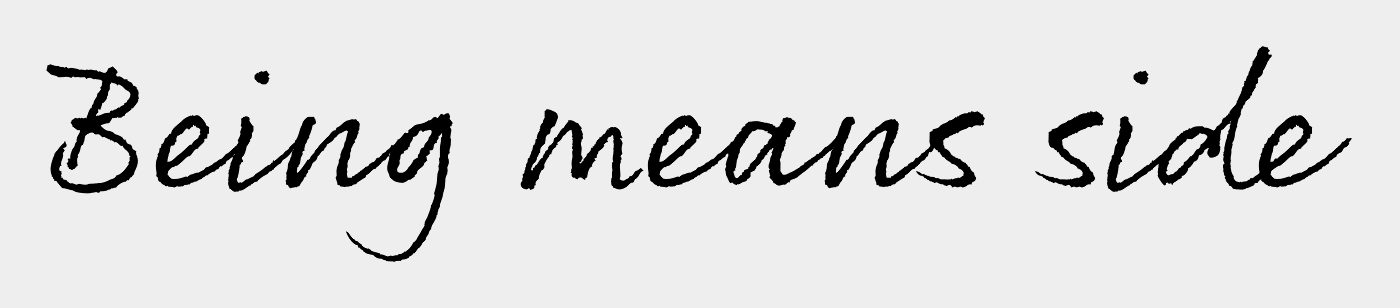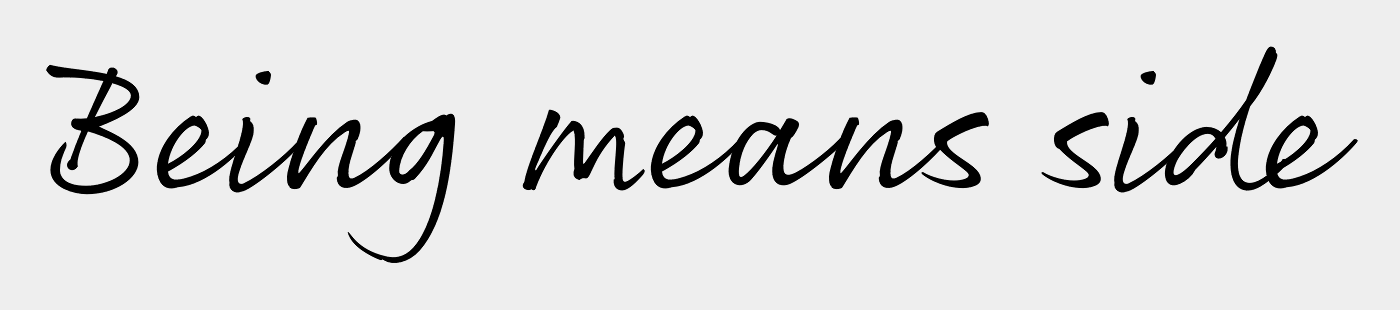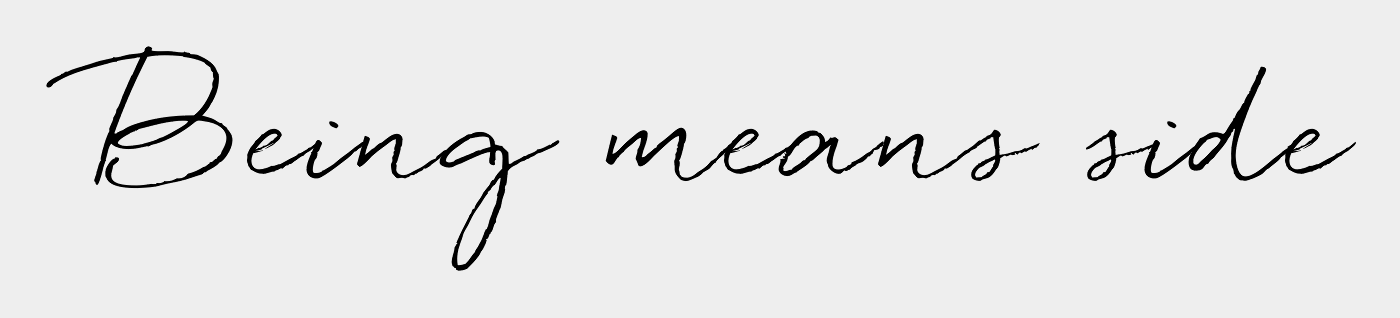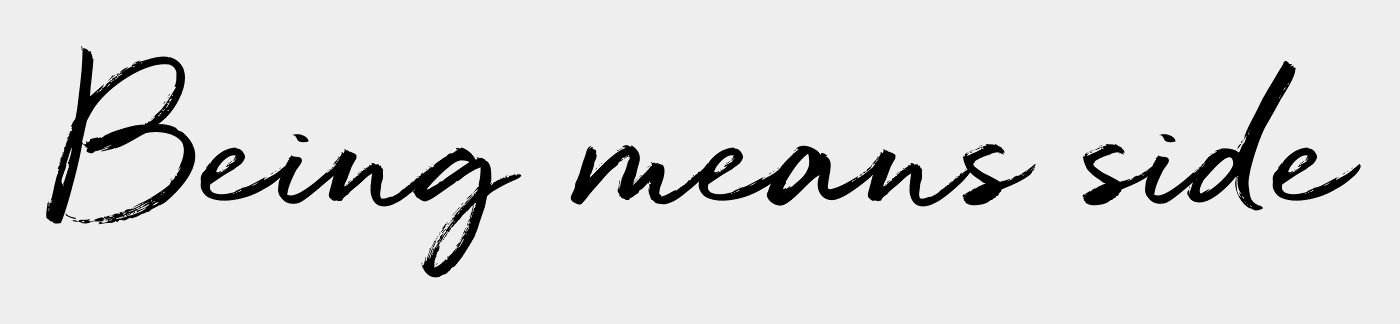
Wie heißt diese Schriftart (Handschrift)
und noch einmal benötige ich bitte Eure Hilfe.
Könnt ihr mir sagen, wie diese Schriftart heißt?
Ich würde sagen, das ist Handschrift, wobei »Being close« kopiert ist.
Wo kommt das her?
Oh, da könntest Du recht haben... ich habe das auf instagram entdeckt
Habe übrigens erst mal when you’re by my fid[d]l[e] gelesen. Ich kenne zu viele Bluegrass-Musiker.
ich les da immer noch fidl … :-o
Willste nicht was Schöneres nehmen?
Jawohl! Die, die Du genant hast, gefallen mir schon exzellent. Und deutlich besser als das von mir hochgeladene! :-) Danke!